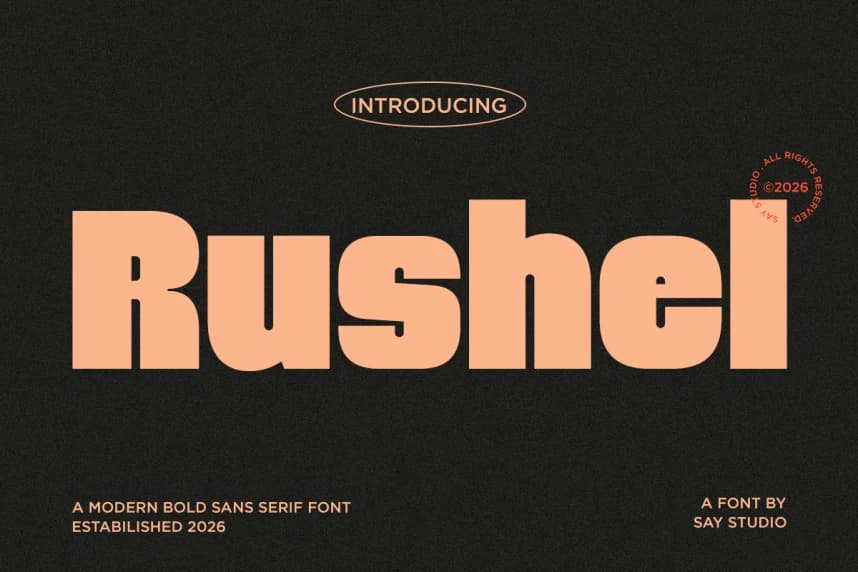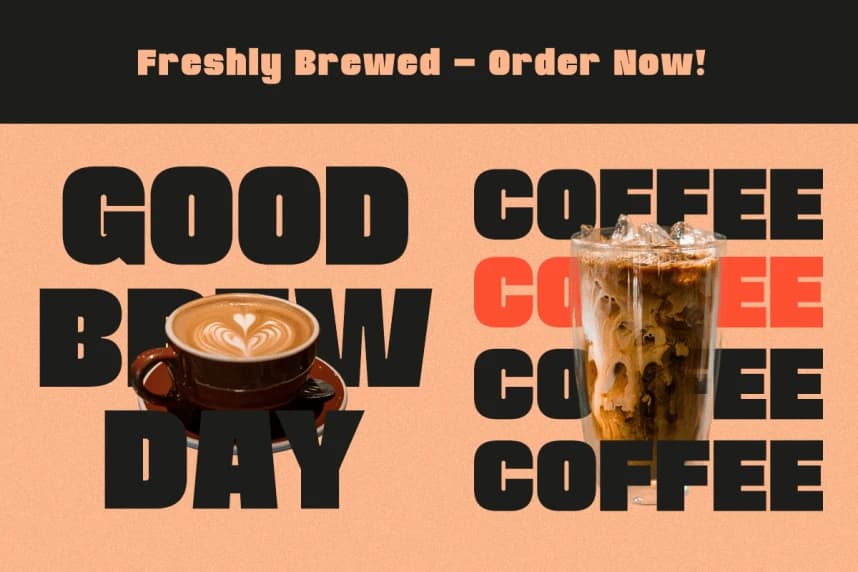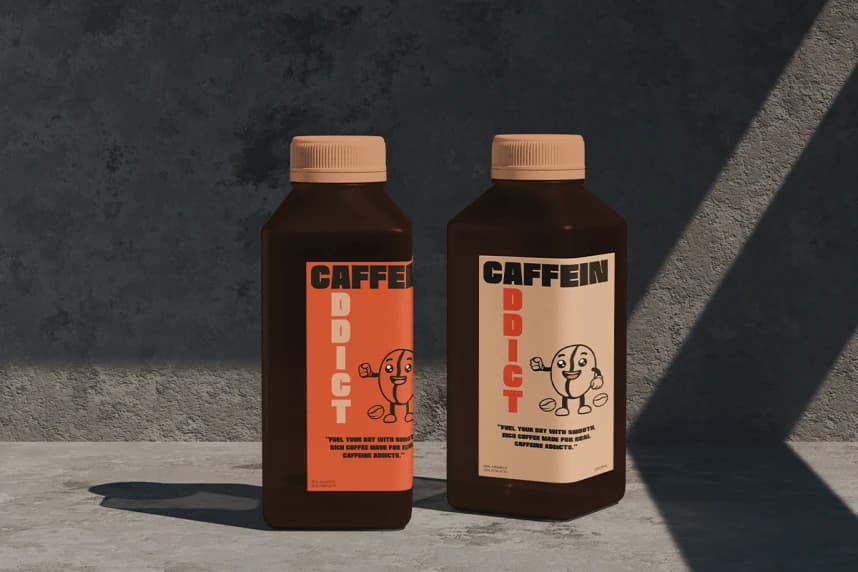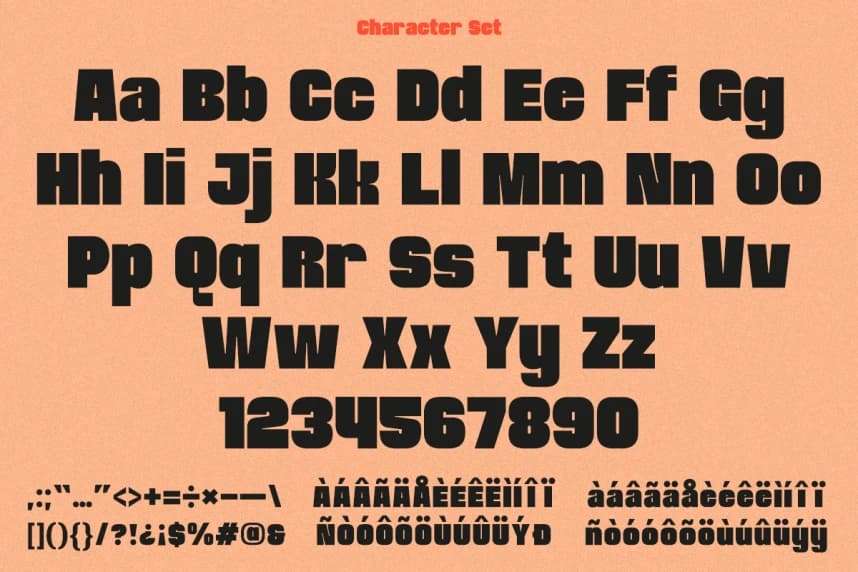
Rushel DEMO Font, güçlü görsel etki ve çağdaş markalaşma için tasarlanmış modern bir kalın sans-serif yazı tipidir. Sağlam yapısı ve kendinden emin oranlarıyla temiz ama güçlü bir görünüm sunar ve dikkatleri anında çeker. Kalın ağırlık ve akıcı eğriler, arasında mükemmel bir denge yaratır.
Rushel DEMO Font, güçlü görsel etki ve çağdaş marka kimliği için tasarlanmış modern bir kalın sans serif fontudur. Sağlam yapısı ve kendinden emin oranlarıyla temiz ama güçlü bir görünüm sunar ve hemen dikkati çeker. Kalın ağırlık ve akıcı kıvrımlar güç ile okunabilirlik arasında mükemmel bir denge kurar ve tasarım uygulamalarında son derece çok yönlüdür.